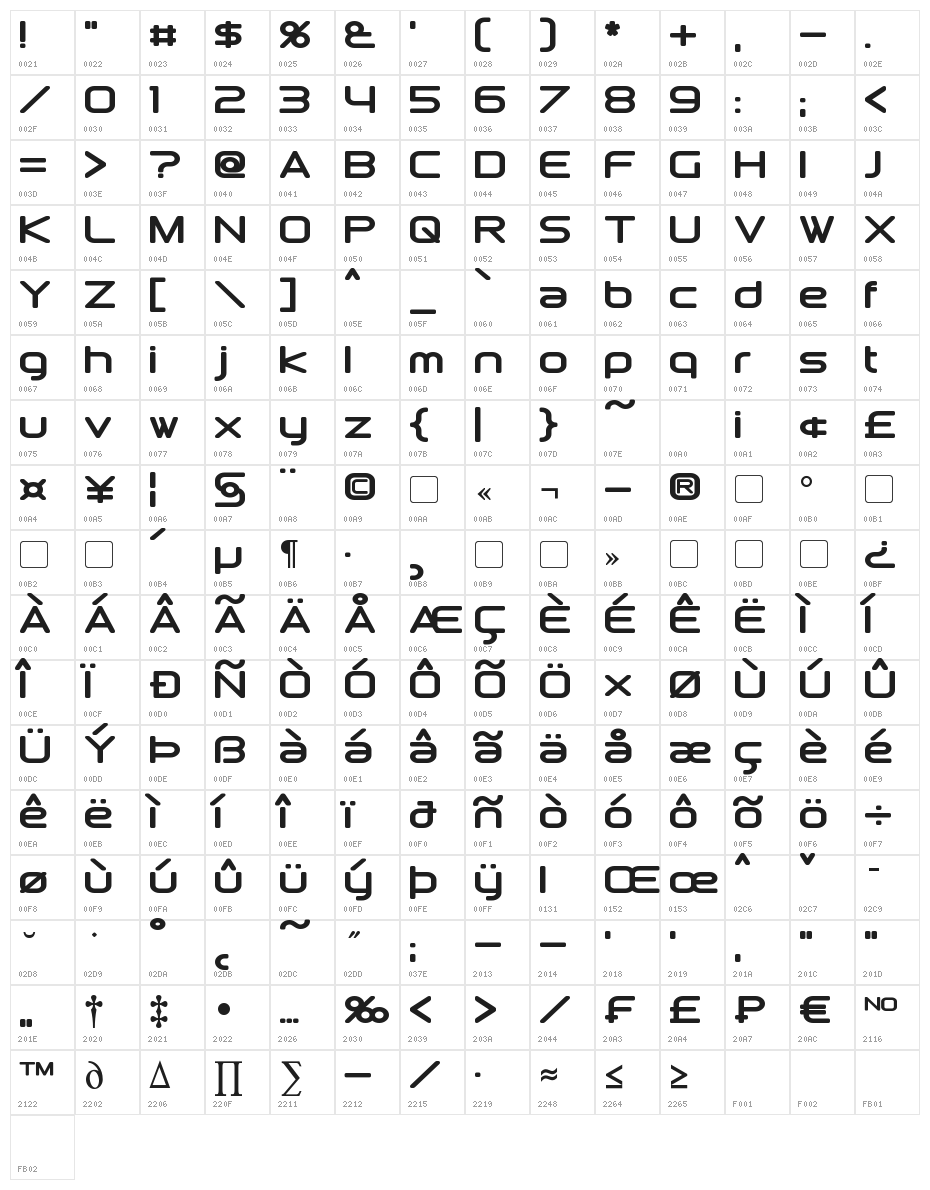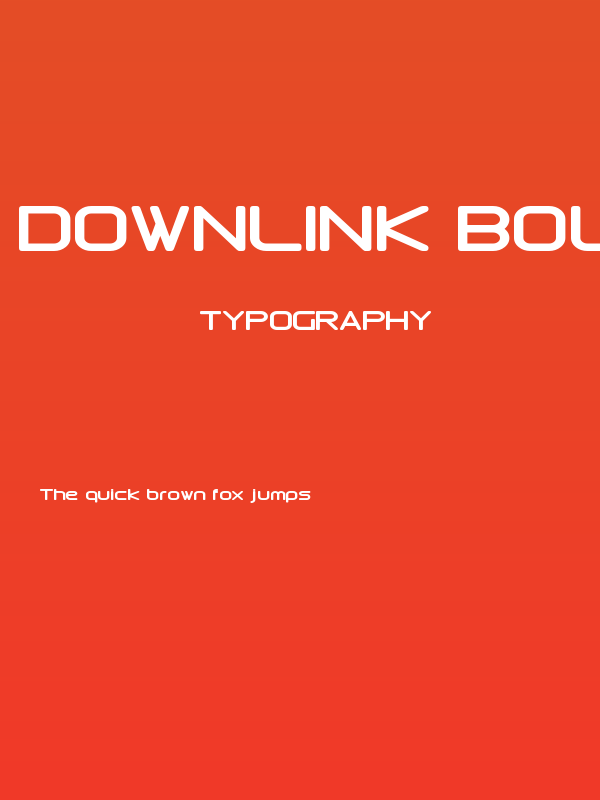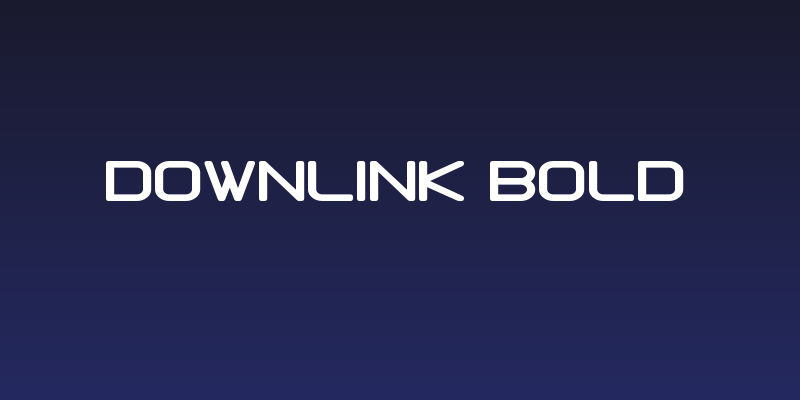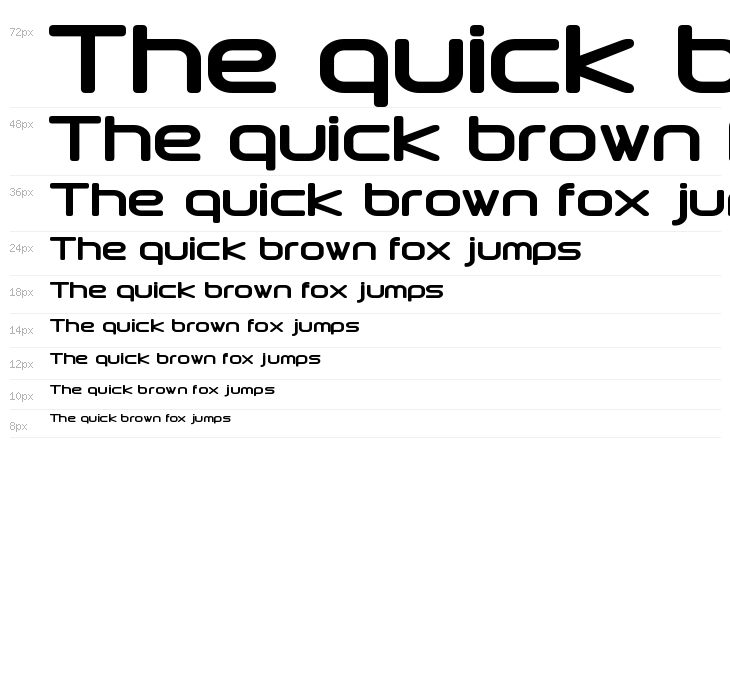
Downlink Bold Font
| Caz de utilizare | Headlines, Logos, Digital Interfaces |
| Proiecte propuse | Ideal for technology branding, modern advertising, digital interfaces, and futuristic design projects. |